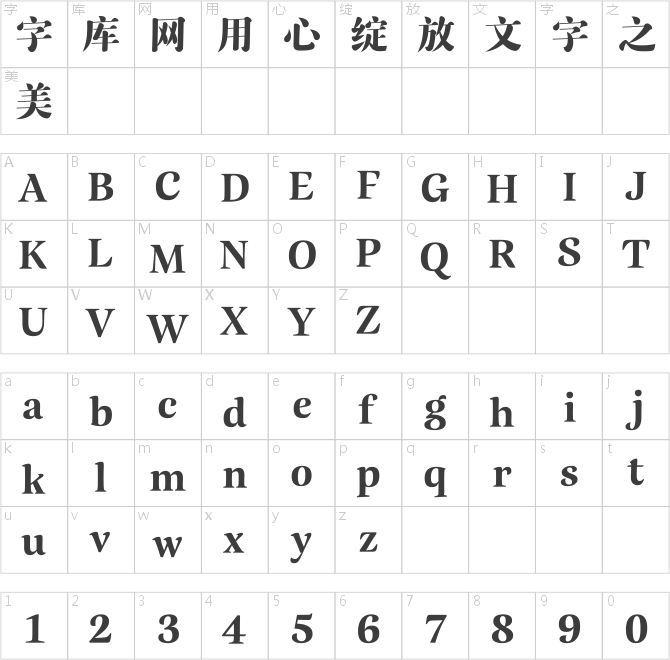
汉仪瑞云妃宋 W 详情页
字体名称: 汉仪瑞云妃宋
汉仪瑞云妃宋 W
汉仪瑞云妃宋 W字体汉仪瑞云妃宋HYRuiYunFeiSongW字库是一款让人赏心悦目、百看不厌的中文字体,适合各类广告和产品包装设计应用,字体大小5.94MB,格式为ttf字体,上传用户是Sakura。,作者/版权方为汉仪字库/战国栋